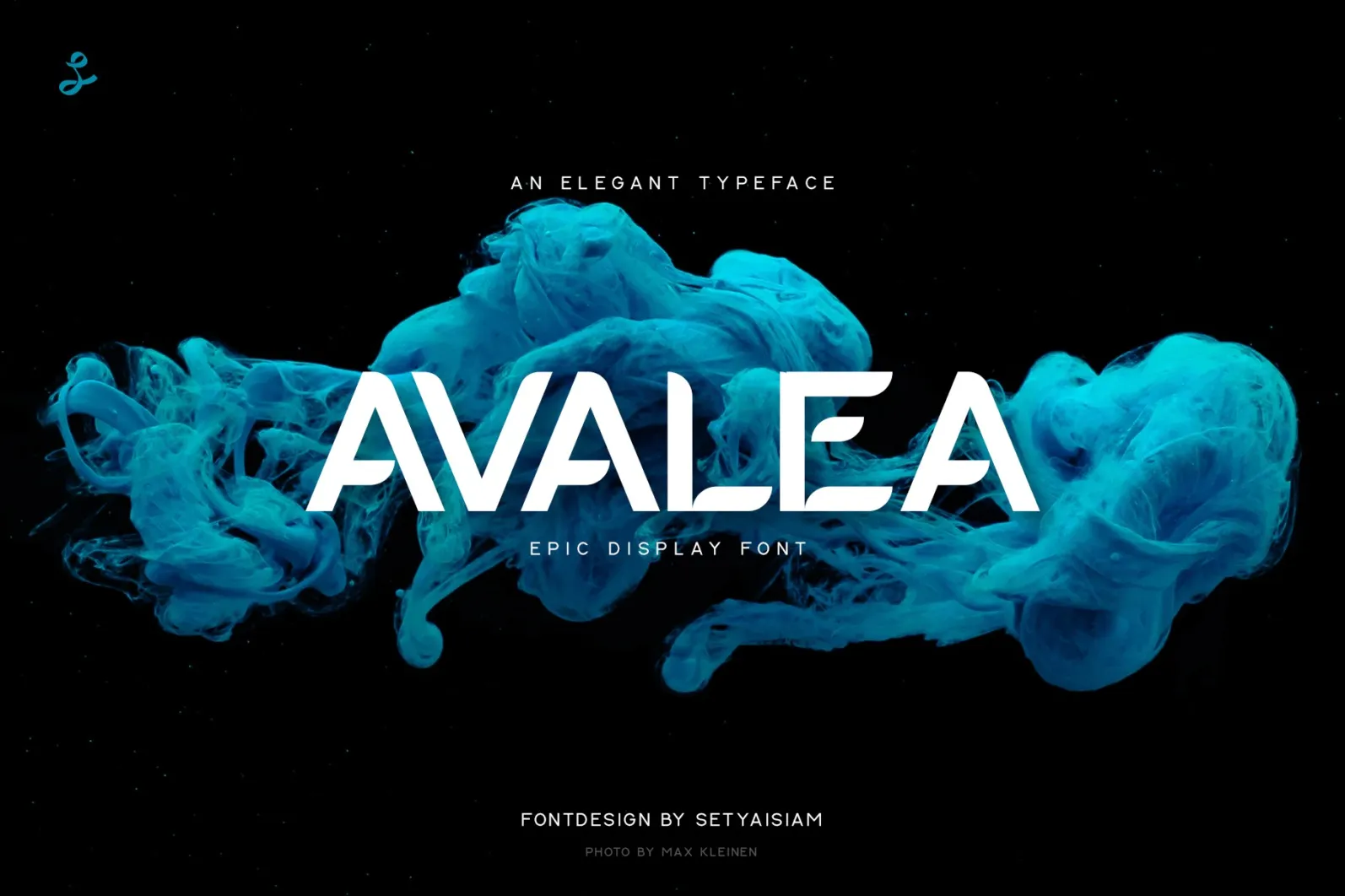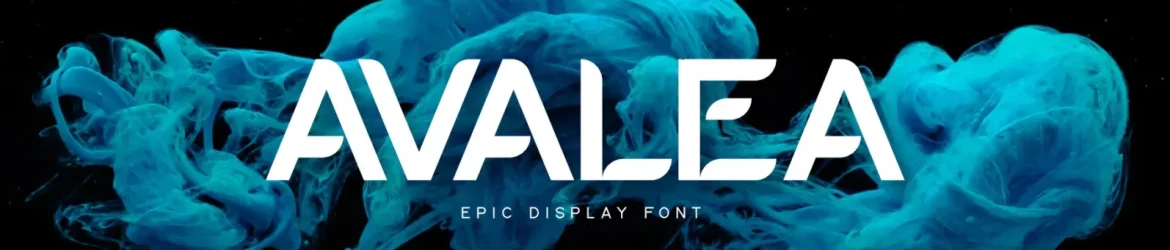
A Avalea Font é uma elegante tipografia bold, redonda e macia projetada por setyaisiam, ideal para aplicação em identidades visuais modernas. Seu estilo é tanto casual quanto sofisticado, fazendo do tipo a escolha perfeita para logos, roupas personalizadas, moda, impressão de materiais e até mesmo para itens de papelaria. Com um design versátil que se adapta a vários ambientes, a Avalea proporciona uma atmosfera moderna e envolvente ao seu projeto. Essa fonte é perfeita para quem busca um equilíbrio entre seriedade e criatividade em seu trabalho de criação visual.